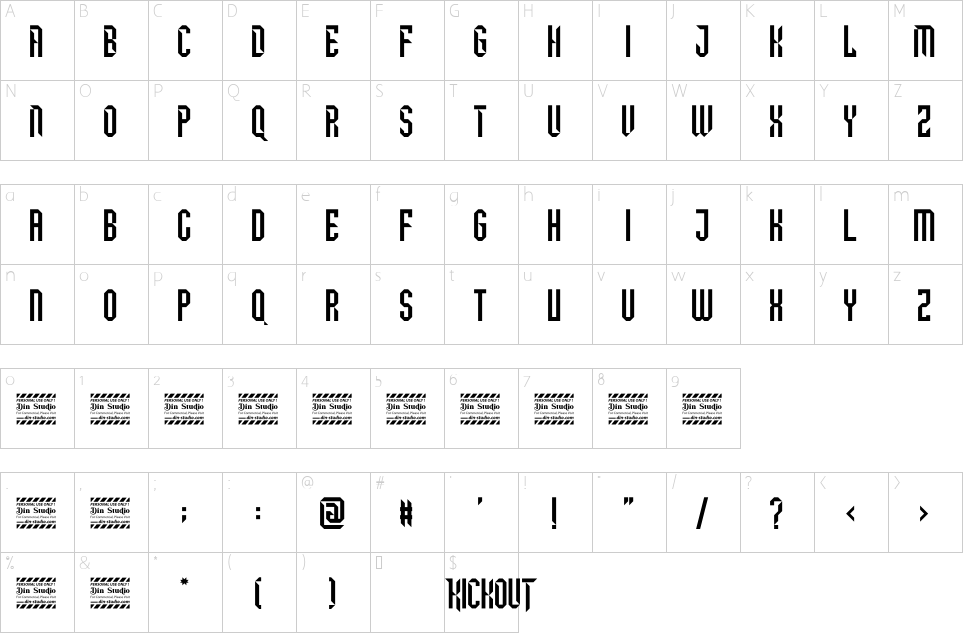
Aqui está uma descrição curta para a página de download da fonte ‘Kickout Font’, adequada aos requisitos fornecidos: A ‘Kickout Font’ é uma opção gratuita e divertida para aqueles que desejam adicionar um toque especial a seus projetos digitais. Desenvolvida pela Din Studio, esta fonte pode ser facilmente usada tanto em dispositivos Windows quanto Mac. Com sua estrutura elegante e simplicidade, ‘Kickout Font’ torna-se uma escolha perfeita para designers de gráficos ou escritores que buscam um visual atraente sem precisar lidar com compras frequentes. Até agora, mais de 3.721 pessoas já baixaram esta fonte confiável e fácil de usar. Instale-a em seus projetos e experimente as inúmeras possibilidades criativas que ela oferece.